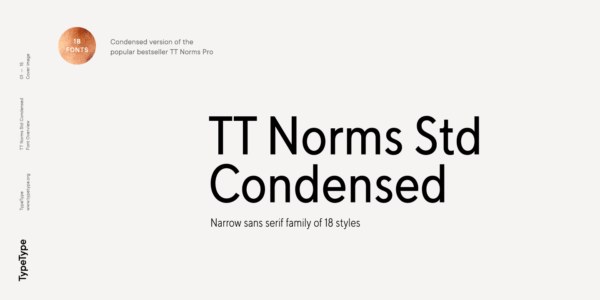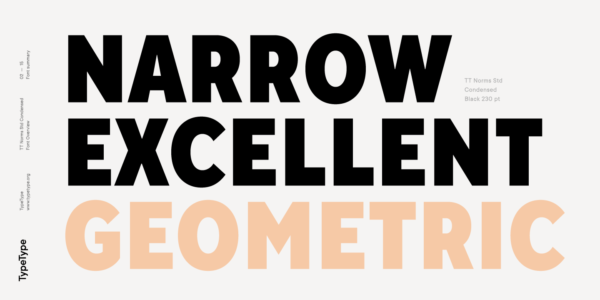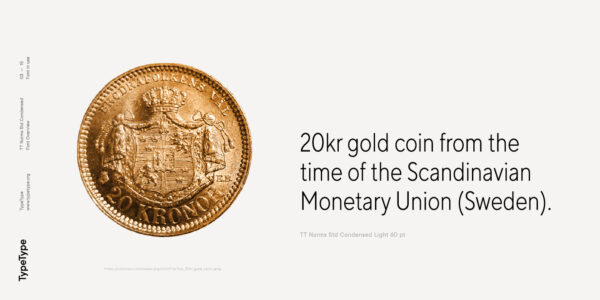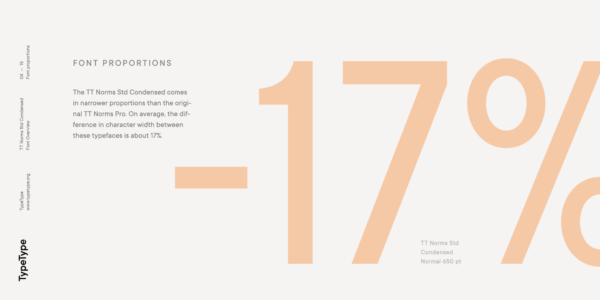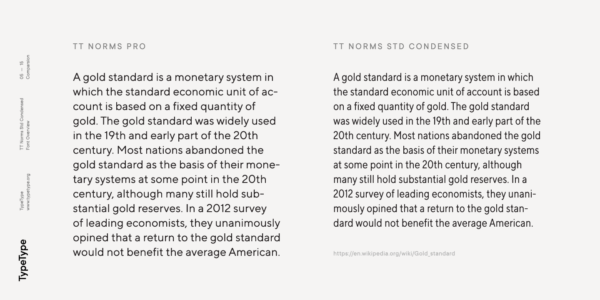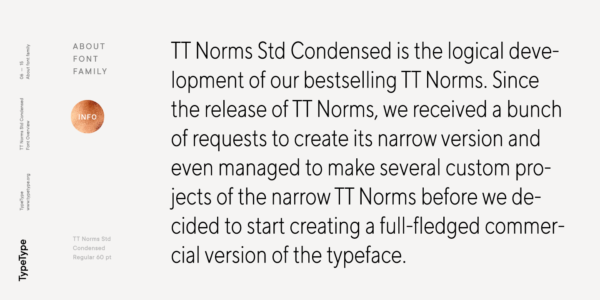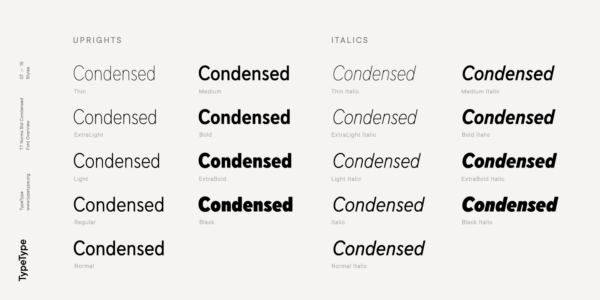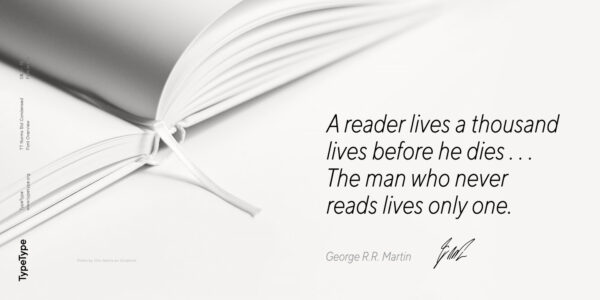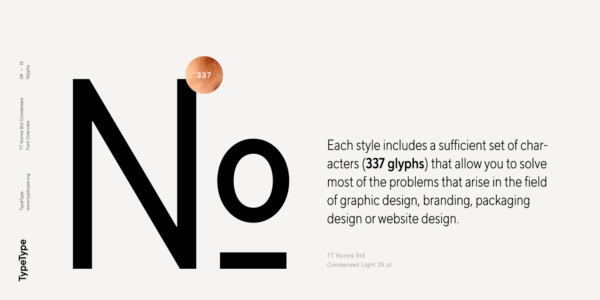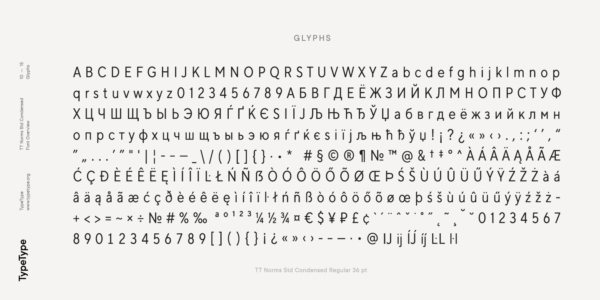
TT Norms® Std Condensed
18 стилей
TT Norms® Std Condensed
TT Norms® Std Condensed — TT Нормс Стд Конденсд
«TT Norms» является зарегистрированным товарным знаком. «Std» произносится как «Стд», является сокращением английского слова standard и переводится как «стандарт». «Condensed» произносится как «конденсд», в переводе с английского — «узкий».
TT Norms® Std Condensed — узкая версия бестселлера TT Norms® Pro. От «прародителя» шрифт унаследовал классические пропорции и универсальность применения.
TT Norms® Std Condensed
TT Norms Std Condensed имеет более узкие пропорции, чем исходная гарнитура
TT Norms Std Condensed является логическим развитием нашего бестселлера TT Norms Pro. С момента выхода TT Norms Pro мы получили кучу запросов на создание его узкой версии и даже успели сделать несколько кастомных проектов узкого TT Norms Pro, прежде чем мы решились приступить к созданию полноценной коммерческой версии гарнитуры.
TT Norms Std Condensed унаследовал классические пропорции знаков
Гарнитура состоит из 18 стилей (9 прямых и 9 италиков)
О гарнитуре TT Norms® Std Condensed
Поддержка языков 130+
TT Norms Std Condensed является логическим развитием нашего бестселлера TT Norms Pro. С момента выхода TT Norms Pro мы получили кучу запросов на создание его узкой версии и даже успели сделать несколько кастомных проектов узкого TT Norms Pro, прежде чем мы решились приступить к созданию полноценной коммерческой версии гарнитуры.
В самом начале проекта мы провели небольшое исследование и протестировали несколько вариантов возможной ширины гарнитуры. Несмотря на то, что TT Norms Std Condensed обладает более узкими пропорциями относительно исходной гарнитуры, он унаследовал классические пропорции знаков, внимание к деталям и дотошную проработку каждого знака в шрифте.
Гарнитура TT Norms Std Condensed состоит из 18 начертаний (9 прямых и 9 италиков). Каждое начертание включает в себя достаточный набор знаков, которые позволяют решать большинство возникающих задач в сфере графического дизайна, брендинга, в дизайне упаковки или в дизайне вэб сайтов.
case | Case Sensitive
tnum | Tabular Figures
dlig | Discretionary Ligatures